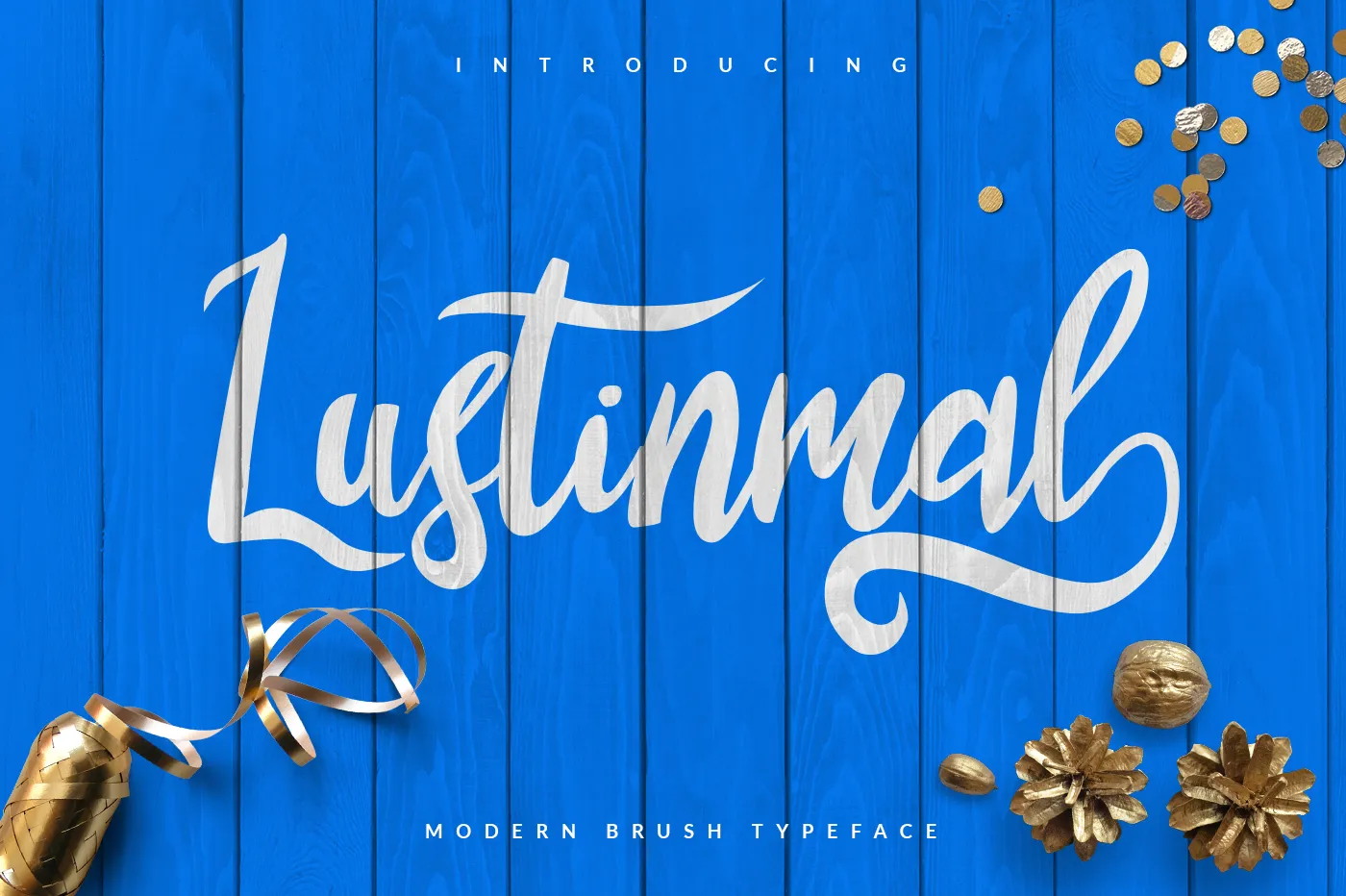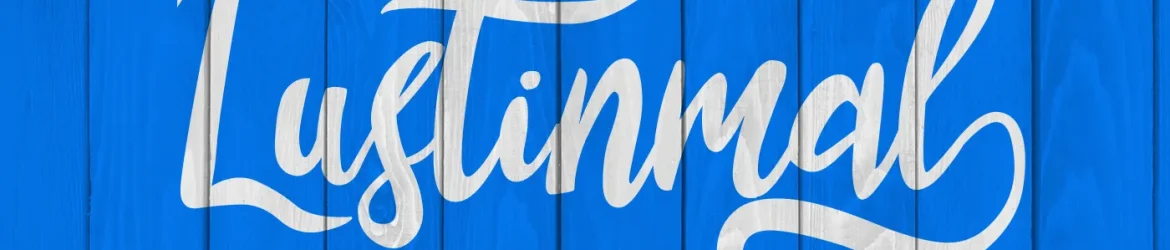
Lustinmal Script Font – Download Grátis
Descubra Lustinmal Script Font, uma maravilhosa fonte criada com folha de caneca fina. Desenhada pelo artista de fontes fontart, essa tipografia única tem linhas grossas que chamam atenção e dão um toque elegante às palavras. Ideal para aplicar em roupas personalizadas, embalagens de produtos ou cartões de aniversário, o Lustinmal Script Font é uma escolha perfeita para qualquer projeto. Com seus atrevidos desenhos no final das letras, ele torna os textos ainda mais interessantes e atraentes. Essa fonte simplesmente brilha em todas as aplicações onde você desejar um toque elegante e sofisticado. Aqui está uma chance única de adicionar personalidade e charme ao seu próximo projeto com Lustinmal Script Font. Esperamos que você goste!